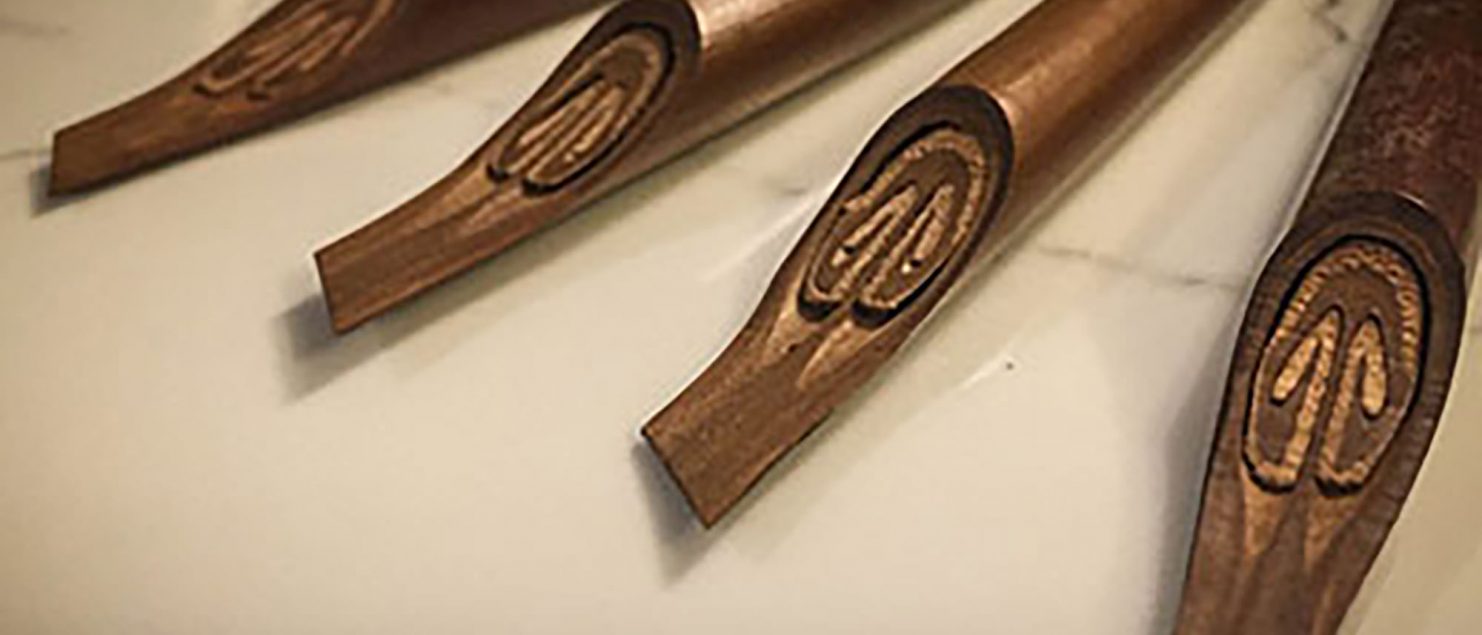
زاویه قلم در خوشنویسی و طراحی تایپفیس (فونت)
زاویه قلمگذارى، یکى از ویژگیهاى اصلى خط است که محور کتابت محسوب میشود و میزان آن براساس مقاصد کاتب و نوع خط متفاوت است. تعیین زاویه قلمگذارى با استفاده از نقطه و یا آغاز الف امکانپذیر است. زاویه قلمگذارى همان چگونگی شروع قلم است که میتواند نسبت به خط کرسی باز یا بسته باشد و در اول حروفی مانند الف، ب و سین قابل تشخیص است. ختم حروف نیز در پایین دوایر و ارسالها و دنبالههای حروف دیده میشود و شکل آن به نوع قلمرانی بستگی دارد به عنوان مثال ممکن است در برخی از خطوط با تمامی قلم پایان یابد و در برخی دیگر با نسبتهای کم قلم خاتمه یابد و اصطلاحا با شمره همراه باشد که معمولا در خوشنویسی کلاسیک انتهای حروف اغلب با نازکی خاتمه مییابد.
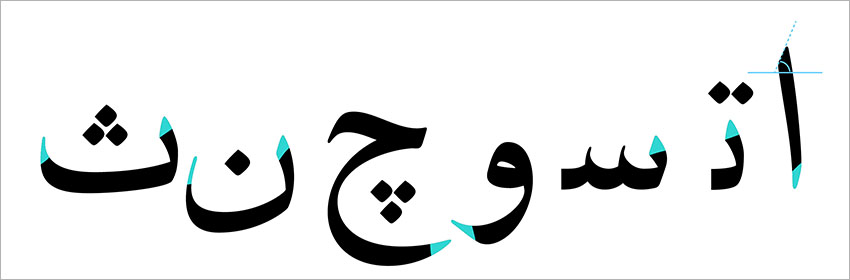
چنانچه زاویه قط قلم افقی یا مورب باشد در کیفیت خط تأثیرگذار است. به عنوان مثال خطوطی که زاویه قط قلم آن محرفتر باشد دارای ظرافت بیشتری است و تنوع پهنا و نازکی در آن بیشتر است و در مقابل هر چه زاویه قط قلم به افق نزدیکتر شود، ظرافتهای خط کاهش مییابد. قلمی که قط آن افقی باشد در هنگام قلمرانی و گردشهای قلم امکان رسیدن به حرکات زیبا و خوشنویسانه در آن کمتر است. از میان خطوط مختلف، قلم محقق و ریحان محرفتر و قلم کوفی صافتر است.
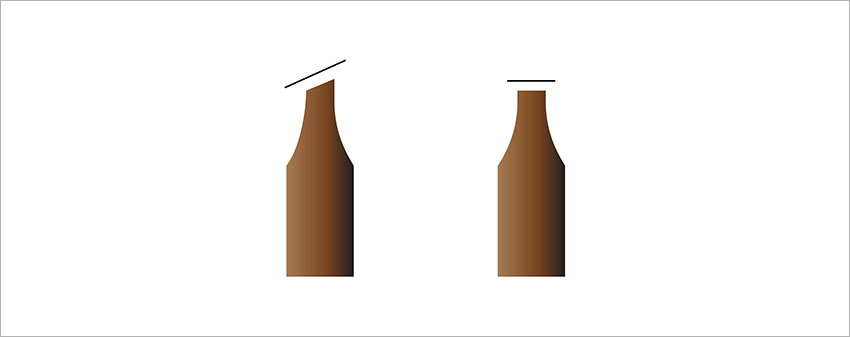
نکته دیگر گوشتی بودن قلم است. هر چه قلم گوشتیتر باشد تنوع گردش قلم و کیفیات خوشنویسانه کاهش مییابد و خط قطورتر میشود.
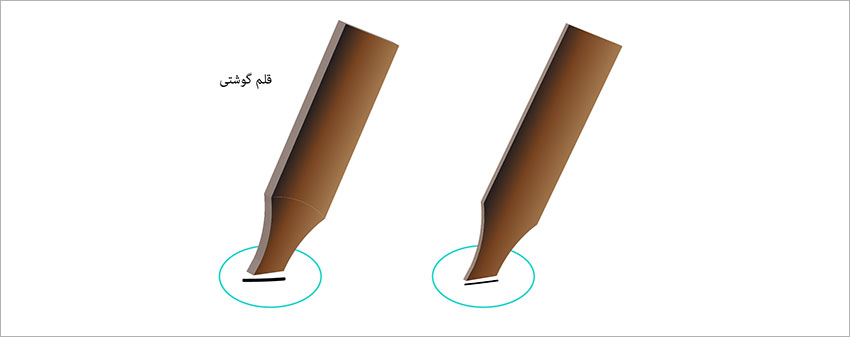
زاویه قلم در فونت نیز به کار میرود و همان شروع حرکت استروک است. کیفیت شروع و پایان استروک بسته به کاربرد فونت و سلیقه طراح تعیین میگردد و یکی از تاثیرگذارترین عوامل در ایجاد لحن یک فونت محسوب میشود. بدین معنا که شروع حروفی مانند سر الف، ب و اشکال مشابه آن متناسب با یکدیگر اند و انتهای حروف نیز متناسب با قاعدهای که طراح تعریف میکند، با یکدیگر هارمونی دارند.
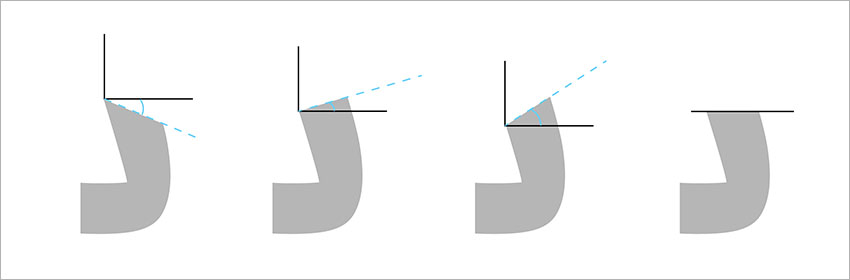
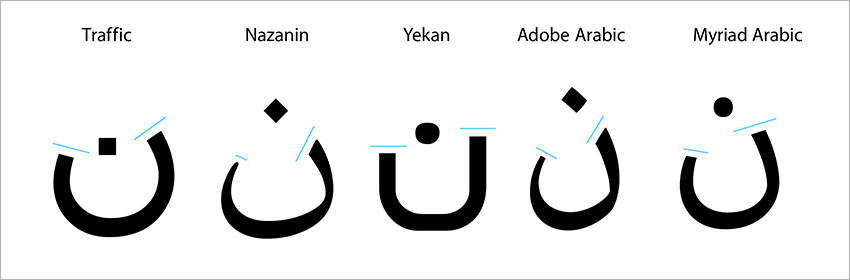
کیفیت شروع استروک علاوه بر زاویه به چگونگی شروع استروک نیز بستگی دارد. مثلا در یک فونت ممکن است شروع استروکها گرد باشد یا از انحنای ملایمی تبعیت کند و یا بدون انحنا و با یک حرکت مورب یا افقی مستقیم طراحی شود.